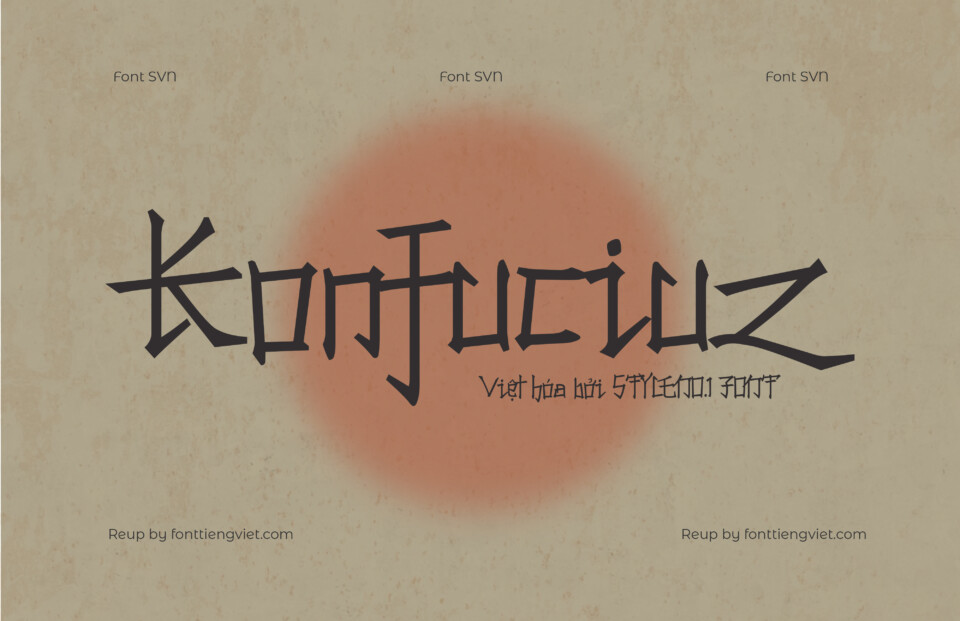
Font Việt hóa SVN Konfuciuz
Trong thế giới thiết kế đồ họa hiện nay, việc lựa chọn một bộ Font Việt hóa SVN Konfuciuz phù hợp đóng vai trò quan trọng trong việc truyền tải thông điệp. Đối với các bạn học sinh và giáo viên, việc tìm kiếm Font Miễn Phí để trang trí bài giảng hay làm báo tường luôn là nhu cầu thiết yếu. Font chữ này không chỉ mang lại vẻ đẹp hiện đại mà còn đảm bảo tính thẩm mỹ cao cho mọi tác phẩm sáng tạo tại Việt Nam.
Đặc điểm nổi bật của Font Việt hóa SVN Konfuciuz
Thiết kế thanh lịch và tinh tế
Bộ Font Việt hóa SVN Konfuciuz sở hữu những đường nét thanh mảnh nhưng vô cùng chắc chắn, tạo cảm giác chuyên nghiệp cho người xem. Đây là lựa chọn lý tưởng cho các bạn muốn thiết kế tiêu đề sách, thiệp mời hoặc các tài liệu học tập cần sự trang trọng. Nhờ quy trình việt hóa kỹ lưỡng, các dấu tiếng Việt được đặt vị trí chuẩn xác, giúp văn bản không bị lỗi hiển thị khi soạn thảo trên máy tính.
Ứng dụng đa dạng trong môi trường học đường
Các thầy cô giáo có thể sử dụng bộ font này để làm mới các slide thuyết trình, giúp bài giảng trở nên sinh động và thu hút học sinh hơn. Với khả năng hiển thị tốt trên cả màn hình và bản in, đây là công cụ hỗ trợ đắc lực cho các dự án sáng tạo cá nhân hoặc tập thể lớp.